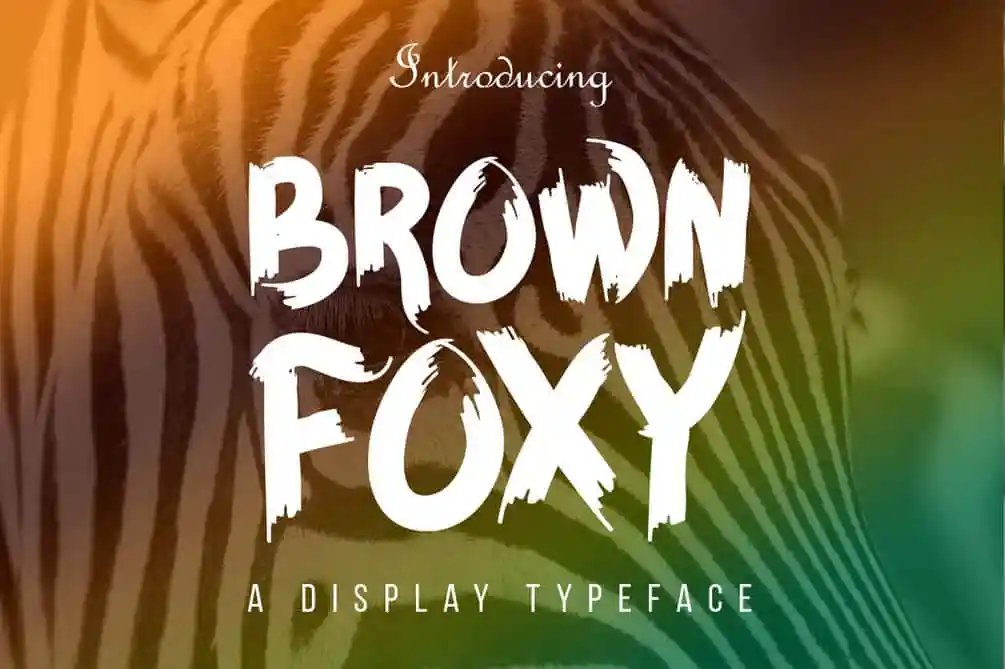
Brown Foxy Font – Download Grátis
Descubra a beleza exuberante da fonte ‘Brown Foxy Font’ na categoria Brush Fonts. Inspirada no estilo artesanal dos desenhos livres e os traços irregulares, essa fonte traz uma atmosfera naturalmente envolvente para seus projetos digitais. Ideal tanto para designers gráficos quanto para aspirantes a criadores de conteúdo online, a ‘Brown Foxy Font’ oferece um ar descontraído e único. Seu design curvilíneo e irregular é perfeito para adicionar uma nota única aos textos, tornando cada palavra em um verdadeiro trabalho de arte. Para usuários que desejam ampliar o seu uso comercial dessa fonte, a Shohail Bhuian oferece suporte atencioso através do email . Não hesite em entrar em contato se tiver dúvidas ou precisar de uma proposta. Visite https://gumroad.com/l/NdTOa para adquirir o seu acesso completo à fonte e garantir seu uso comercial. Agora, é hora de explorar a versatilidade desta fonte única e experimentar a essência da arte livre com um toque de personalização.